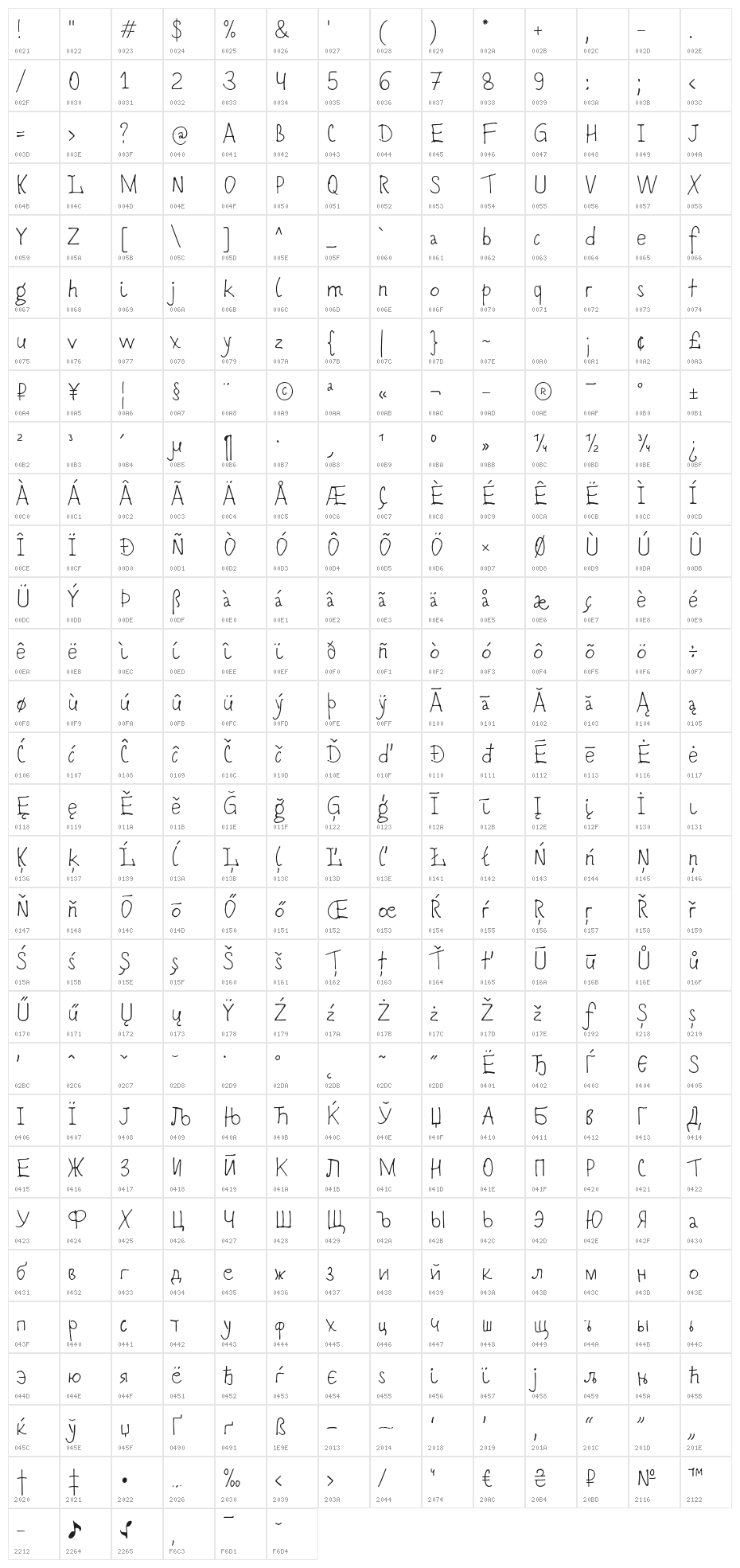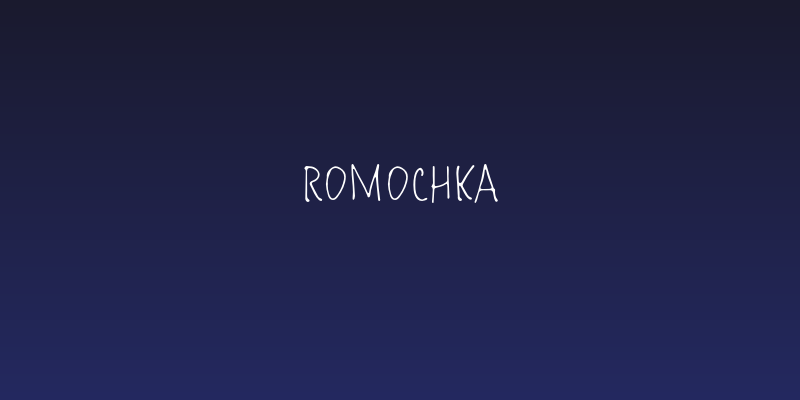
Romochka Font
| النمط العام | Casual |
| حالة الاستخدام | Headlines, Logos, Invitations |
| مشاريع مقترحة | Ideal for children's books, greeting cards, casual invitations, and creative branding. |